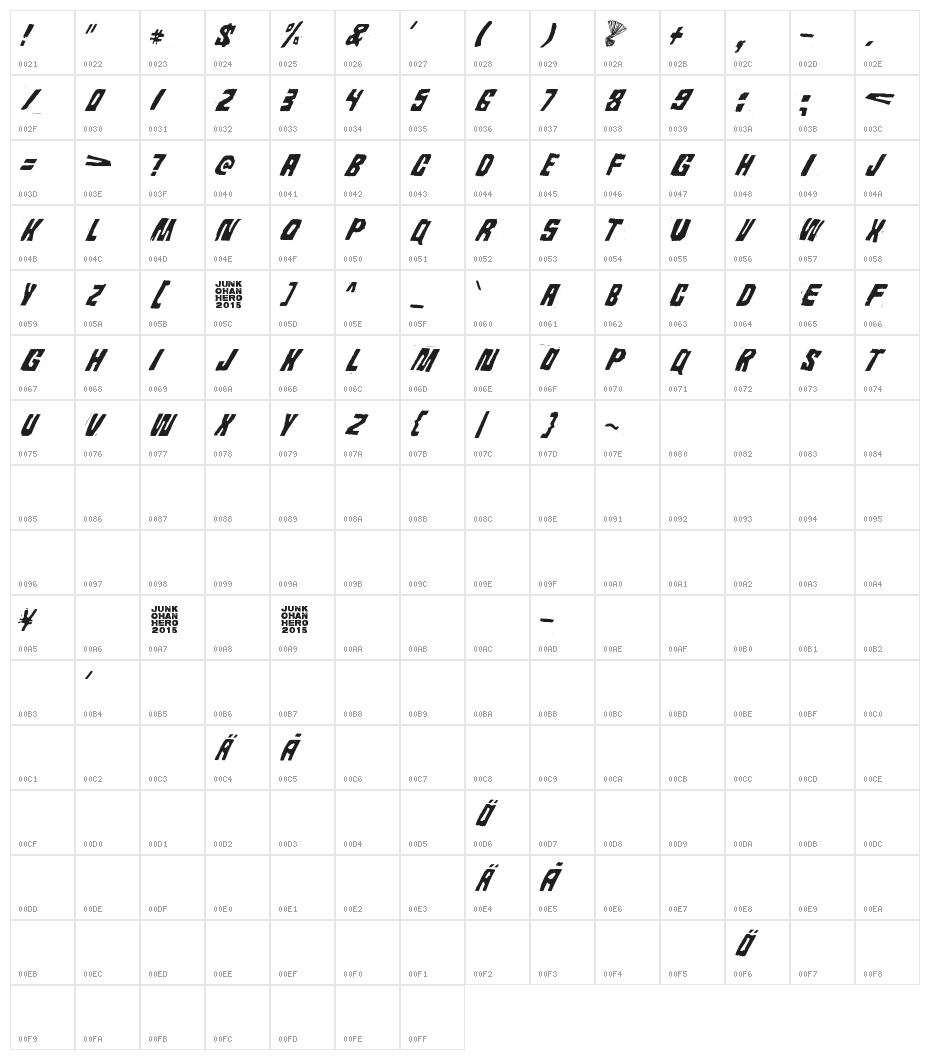
Androidi Pisa Font
✎ Distorted Eroded
| النمط العام | Futuristic, Industrial |
| مشاريع مقترحة | Ideal for sci-fi themed designs, video game titles, posters, and branding that requires a modern and edgy look. |